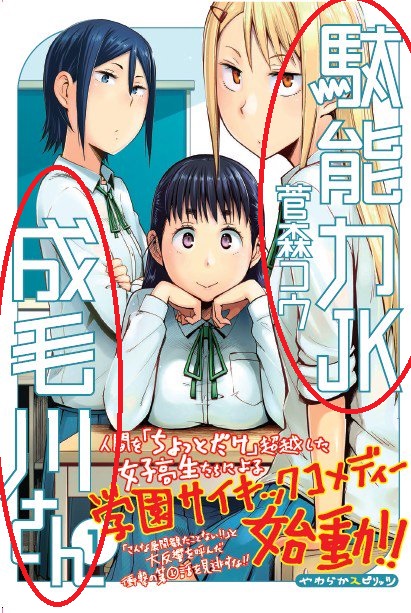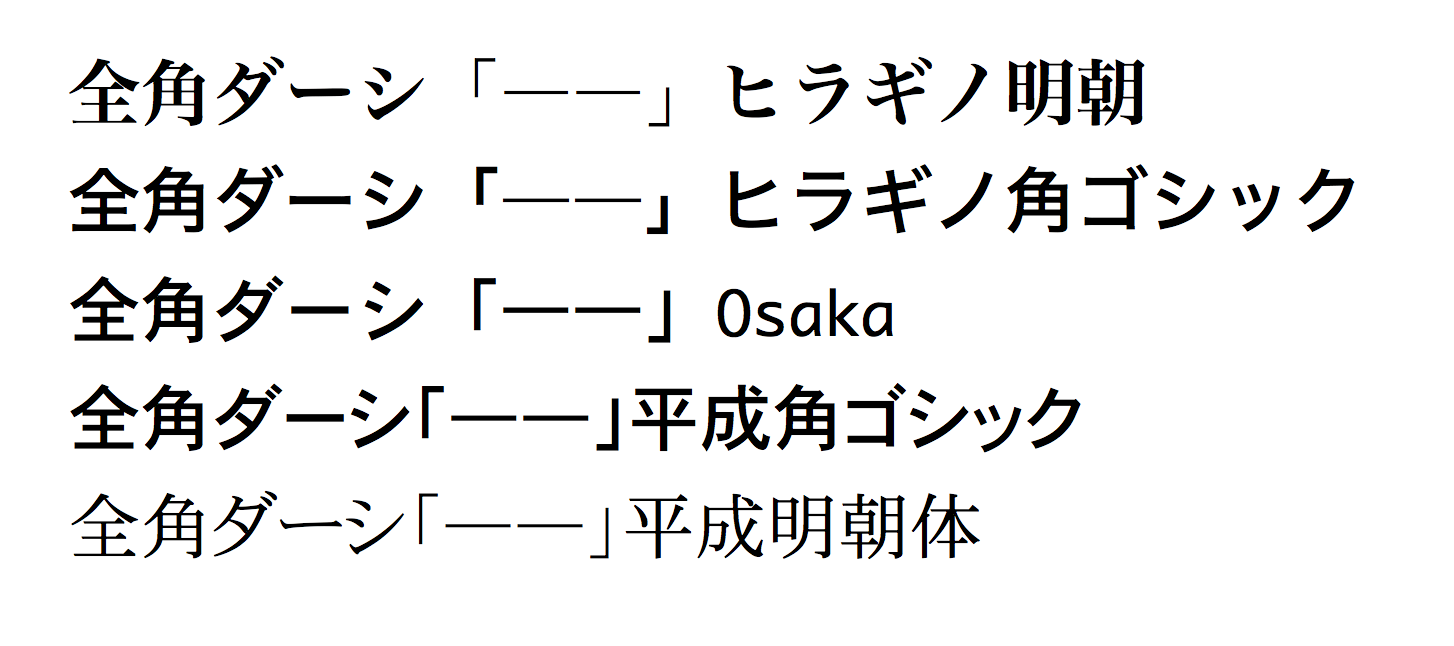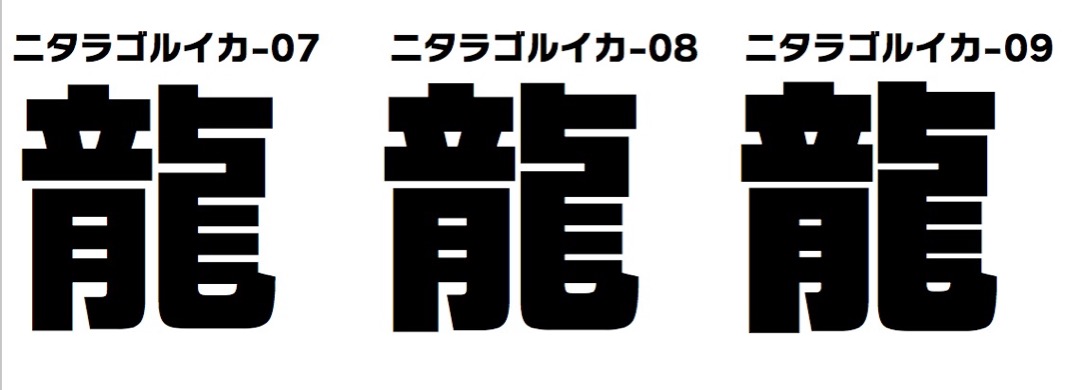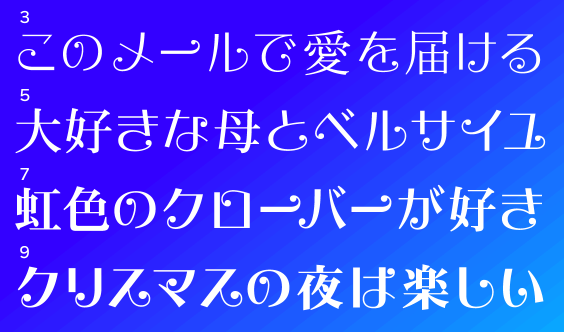
学校関係の仕事を主にしております。最近名前ではしごの高とか立崎とか、点のついている丈とか、いわゆる外字?を要求されることが多くなっています。イラストレータで作字して使っていますが、外字のフォントがあれば使いたいと思っています。よく名前で使うのは平成明朝3W・5W・7W、平成角ゴジック5W・7Wです。MacOSは9.2.2です。何を購入したらよいかわからないので教えて頂ければ幸いです。よろしくお願いいたします。
たとえば、ここで販売している平成明朝フォント。
おためしプレビューという欄に、必要な文字を打ち込むと表示してくれます。
購入される前に確かめるといいですね。
ちなみに「はしごの高()とか立崎()」は表示されました。
小さな文字が出ない…?  bach  2020年3月9日(月) 16:13  Mail
先ほど「キャピレラ」をダウンロードしたのですが、「きって」や「はっしゃ」などの小さな文字が打てないのですが、何故か分かる方いらっしゃいますか?
KITTEと打ったりLを使ってもダメでした。
ダウンロード仕直した方がが良いのか、それとも何か方法があるのか、わかる方がいらっしゃいましたら教えて頂けますでしょうか?
タイプラボの無料フォントには、濁音・半濁音・拗促音が含まれておりません。
このフォント名分かりますか?  みき  2020年3月5日(木) 6:33
漫画で使われていたのですが
このフォントが可愛くて、フォント名を知りたくなりました!
探してみたのですが、私の探し方では見つけることが出来ず…
知っている方がいらっしゃったら、教えて欲しいです!
モリサワの「竹」だと思います。
数日前、UDフォントを調べていてモリサワのページを訪れていたのに
その時は出会えませんでした。
セプテンバーLが大好きで、使わせて頂いています。
これからも好きなフォントを探していきたいと思います!
この画像の、"PAR5"や、"142.44y"の部分に使われているフォントは何か、知っていたら教えてほしいです..
さとう様
返答ありがとうございました。
Officeのアップデートや,FontBookを使って必要以外のフォントを使用停止にしたりもしましたが,無理でした。
フォントの買い直しを検討しています。セプテンバーNが使えることは確認していますが,あられやアニト・キャパニトで現在ダウンロード販売されているものは,フォントパック2008と同じものなのでしょうか。
さとうゆたか  2019年5月2日(木) 21:47 [修正]
満太郎さん、こんばんは。
あられやアニト・キャパニトなどの、フォントパック2008にも入っているフォントは、セプテンバーNやルイカ系フォント(こちらはOS9では使えません)とは、すこし仕様が違います。
現在の無料版で確認してほしいですが、これまでの満太郎さんの情報ですと、あられやアニト・キャパニトなどは、MS Office 2016 for Macでは動かないと思います。
試してみます  満太郎  2019年5月12日(日) 22:14 [修正]
さとう 様
回答ありがとうございます。アニトやあられなどの無料版は,濁音などがないことをのぞけば,フォントパック2008と同じものなのですね。
まずは試してみて,使えないようなら,セプテンバーNのみ購入しようかと思います。
お試し用無料フォントについて  スフィア  2018年9月30日(日) 20:26
Windows10にアップグレードした後、再DLしてハッピールイカを使用させていただこうと思ったのですが、TrueTypeフォントファイル内のテキストの「Windowsでコンピューターの世界が広がります」が「Windows コンピ ーターの世界 広 ります」となってしまっています。
アップグレード前はちゃんと使えていましたが、破損したのでしょうか?
さとうゆたか  2018年9月30日(日) 20:57 [修正]
無料のお試し用フォントは、先月に仕様変更いたしました。
無料フォントに含まれる「ひらがなカタカナ」は、清音のみとなりました。
ですから、その表示は正常です。
えれがんとフォントを使って動画の字幕に使いたいですが、  JR813系  2018年8月19日(日) 15:45  Mail
ご質問しますが、よろしいですか?
えれがんとフォントを使って動画作成ソフトの
ウィンドウズムービーメーカの
の字幕に使いたいですがよろしいですか?
また、使う際は許可やそのフォント名を表記は必要ですか?
さとうゆたか  2018年8月19日(日) 16:01 [修正]
Q&Aのページは、読んでいただけたでしょうか?
普通に字幕に使うのでしたら、構いませんよ。
作者名とかフォント名も記載しててくれたら、その動画を見た他の人も参考になるので、できたら入れてください。
Q&Aのページ↓の、映像作品のところを読んでください。
よろしくお願いいたします。
こういうフォントってありますか  kanabun  2018年5月27日(日) 10:33  Mail
失礼します。
wordで チラシを作っているのですが、
添付画像の 見本のタイトルにある
『認知症予防講座』
のような書き方が 「文字装飾」では実現できません。
こういう装飾フォント って 市販されているのでしょうか?
よろしくお願いします。
さとうゆたか  2018年5月27日(日) 10:55 [修正]
リコーが販売している「 HGインライン丸ゴシックE」じゃないでしょうか。
kanabun  2018年5月27日(日) 11:41  Mail [修正]
確認しました。
商用フォントで あるんですね
さっそくありがとうございました。
とも  2018年3月22日(木) 13:01
はじめまして。
今ほどニタラゴルイカの体験版をダウンロードさせて頂きました。
4文字必要なのですか、欲しい文字が2つ無かったので購入を考えております。
しかし、欲しい文字の画数が多いため実際どんな風に見えるのか不安に思っております。
(9が良いのか8が良いのか等)
そこでら写真でも良いので、実際に見せていただくことは無理でしょうか。
高い買い物ですので、悩んでおります。
ぜひご検討頂ければと思います。
欲しい文字のうち1つは【龍】です。
よろしくおねがいします。
サンプル画像  さとうゆたか  2018年3月22日(木) 13:42 [修正]
ウェイト07・08・09の画像です。
参考にしてください。
2倍ダーシ「——」が繋がらないのは…  takumi  2017年3月21日(火) 10:14  HP [修正]
旅先からご返答ありがとうございます(笑)。
>罫線文字「───」「━━━」を使えば繋がります…。
あ、確かに代用できますね。
罫線素片は使える(繋がる)ようにできているなぁと思いながら、気付きませんでした…。
今後もタイプラボフォント、末永く使わせて頂きます。
旅の方も楽しんでくださいね。
さとうゆたか  2017年3月25日(土) 9:23 [修正]
追加情報…です。
私は、ずっとMacを使っているので、MacOS標準フォントのOsakaやヒラギノ書体を参考に、書体を制作していました。
その影響ですね…。
次期ルイカ系書体をアップデートする時に忘れていなければ、繋がるように直したいと思います…。
ルイカ系は修正済み  さとうゆたか  2017年11月17日(金) 14:19 [修正]
「ダーシ」が2個並んだときの表示。
今年アップデートしたルイカ系フォントでは、すべて繋がるようになっています。